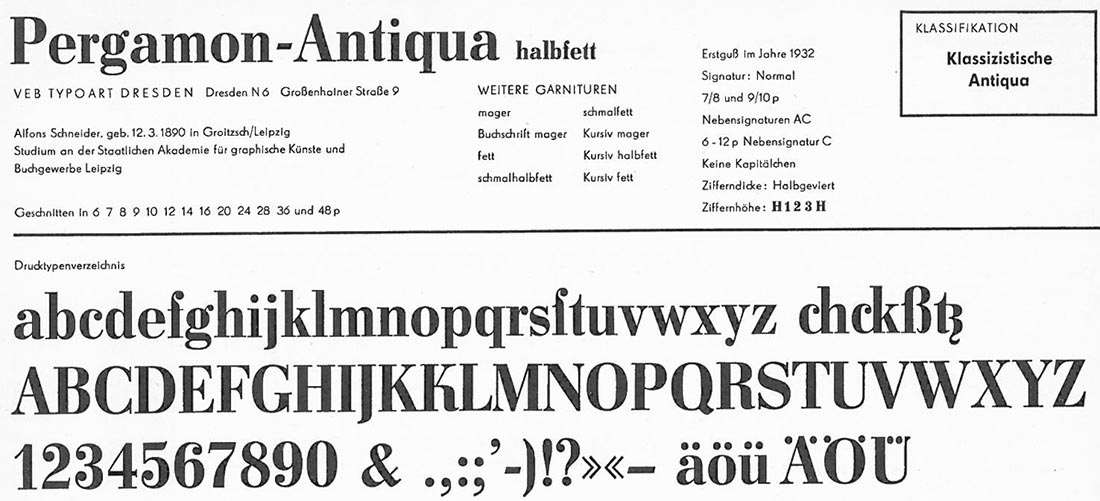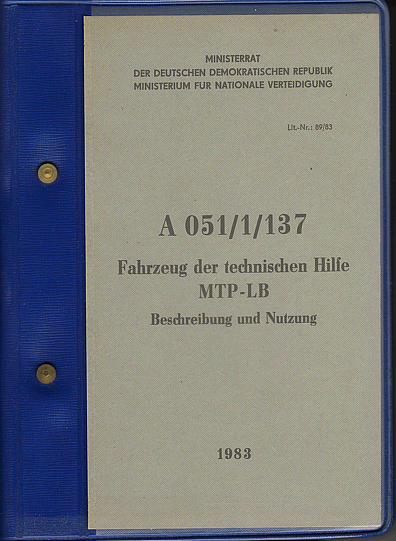
NVA-Dienstvorschrift
ich muss Euch leider nochmals stören. Ich bin auf der Suche nach dem Schriftnamen, mit dem die NVA-Vorschriften gesetzt wurden (nur der Schmutzumschlag).
In den Jahren 1988/89 war es zunehmend die Magna. Das Beispiel im Link zeigt eine andere. Wer kann helfen? Der Textteil wurde mit Schreibmaschine (vglb. Cella) geschrieben.
Kopf (Ministerrat …) Super, Titel Pergamon.
… und sogar einigermaßen ausgebaut, ich weiß von acht Schnitten.